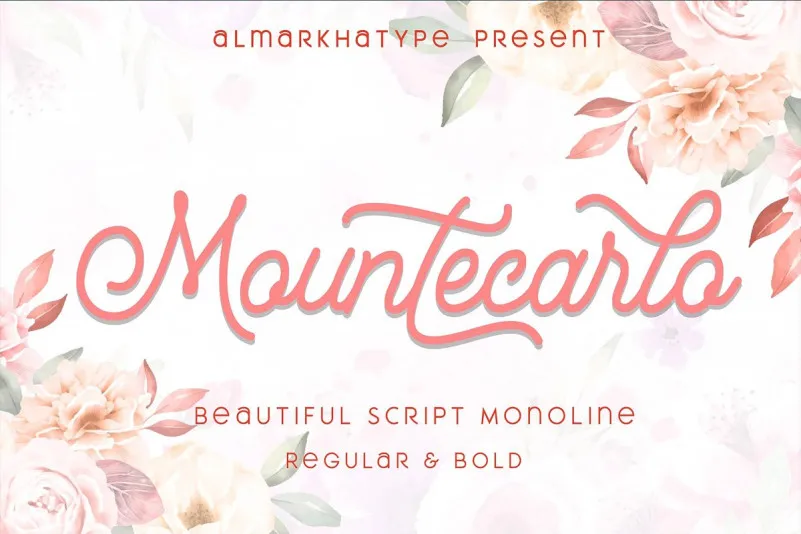
Mountecarlo Monoline Script Font – Download Grátis
Agradeço a sua atenção à Mountecarlo Monoline Script Font. Esta é uma beleza, estilo vintage e linhas monolíneas com movimento e elegância que dá ao seu trabalho um aspecto cuidadosamente desenhado à mão, sem qualquer esforço necessário. O Montecarlo Script Monoline é um belo tipo de linha única, perfeito para a criação de logotipos, marca, design de roupas, sinais, cartazes e convites de casamento, apenas para mencionar alguns destes muitos usos. Esta fonte preserva o meu estilo nas letras que foram inicialmente baseadas em minha própria escrita e depois cuidadosamente aperfeiçoadas para criar uma série de caracteres consistentes. O seu toque manufatureiro e a personalidade dão-lhe um toque autêntico.